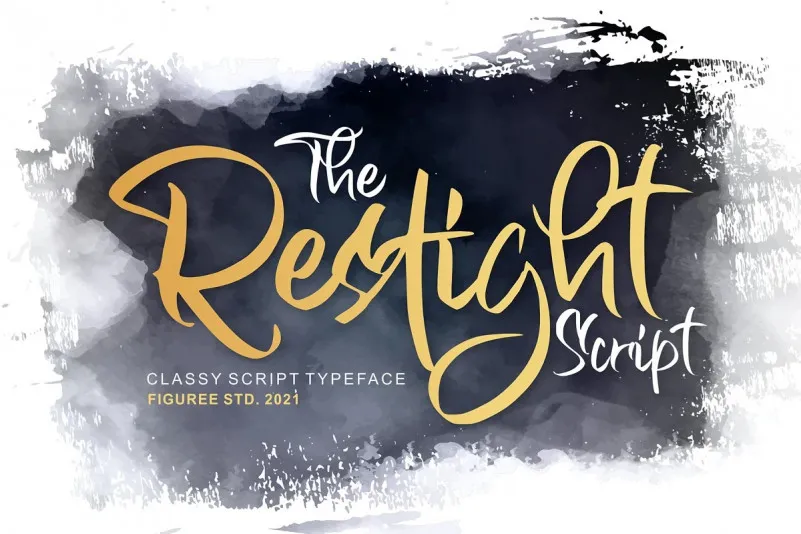
A Restight Font é uma abordagem fresca do mundo do design tipográfico, criada pela figurae studio para quem busca adicionar um toque autêntico e chamativo aos seus projetos digitais. Este script brush é uma mistura de grafismo manual com estilo casual e forte, oferecendo um tipo elegante que pode se adaptar a diversos campos do design, desde logotipos até embalagens customizadas e posts nas redes sociais. Seu design moderno e atemporal garante que seu projeto seja notado, tornando-se uma escolha perfeita para designers buscando incorporar um toque autêntico no seu trabalho. A Restight Font é a escolha ideal para quem deseja dar um gás novo à sua identidade visual, trazendo ao design algo único e envolvente que chama atenção em qualquer plataforma digital.